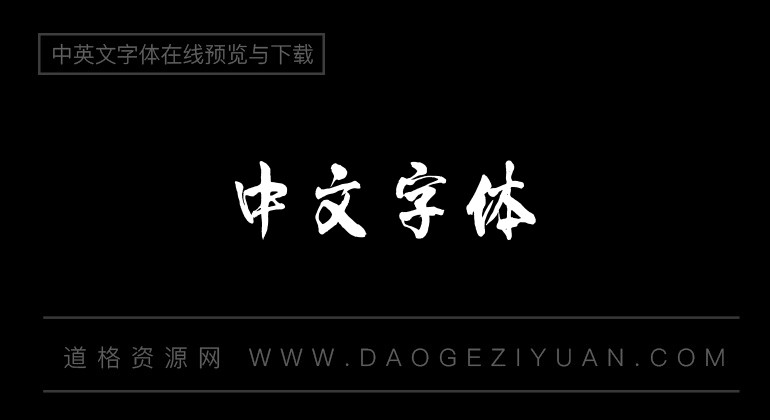
剑客毛笔行书
剑客毛笔行书是一种传统的汉字书法字体,它以苍劲有力的笔画为特点。剑客毛笔行书的笔画粗细有致,笔画挥洒自如,整体看起来有力而有灵气,充满了动感。它的字体表面有着厚重的纹理,字体的边缘也有着锋利的线条,显得非常有力量。此外,剑客毛笔行书还有一种特殊的技巧,即“抹面”,它能够使字体显得更加清晰,更加生动。
剑客毛笔行书是一款非常不错的手写艺术字体,具有很好的视觉感,适合于文化类的宣传设计、商业类品牌的广告和产品包装设计以及个性化文字排版等较多场景。